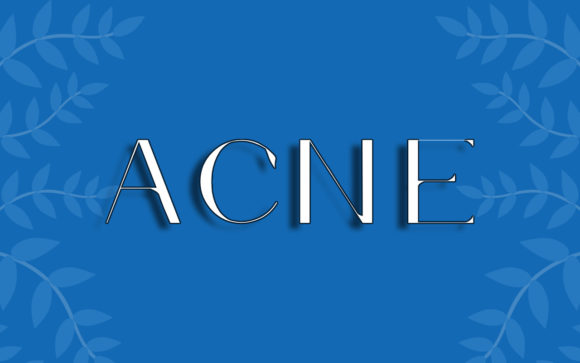
Acne
Acne – A Fonte Display Que Transforma Qualquer Projeto
Se você está em busca de uma tipografia que una clean design e versatilidade, a Acne de Viktor Hammarberg é a escolha perfeita. Desenvolvida como uma fonte display, ela apresenta caracteres bem equilibrados, modernos e altamente legíveis, capazes de se adaptar a diferentes estilos visuais sem perder a identidade.
Por que a Acne se destaca?
- Design limpo e contemporâneo – Cada glifo foi cuidadosamente trabalhado para garantir linhas suaves e formas harmoniosas, evitando excessos que possam distrair o leitor.
- Alta adaptabilidade – Seja em branding, pôsteres, capas de livros ou interfaces digitais, a Acne se encaixa perfeitamente, proporcionando um toque de sofisticação sem esforço.
- Variedade de pesos – Com opções que vão do regular ao bold, você pode criar hierarquias tipográficas claras e dinâmicas em seus projetos.
- Legibilidade impecável – Mesmo em tamanhos menores, os caracteres mantêm clareza, o que a torna ideal para títulos, chamadas de atenção e até pequenos blocos de texto.
Como usar a Acne no seu próximo projeto
Incorpore a Acne em:
- Identidade visual de marcas que buscam um visual clean e moderno.
- Pôsteres e flyers de eventos, onde a tipografia precisa chamar atenção instantaneamente.
- Web design, especialmente em hero sections e chamadas de ação (CTAs).
- Embalagens de produtos premium que necessitam de um toque de elegância.
Com sua estética bem equilibrada e a habilidade de se adaptar a uma ampla gama de aplicações, a fonte Acne prova ser um recurso indispensável para designers que desejam elevar a qualidade visual de seus projetos. Experimente adicioná‑la ao seu repertório criativo e veja como ela traz vida e personalidade às suas ideias.